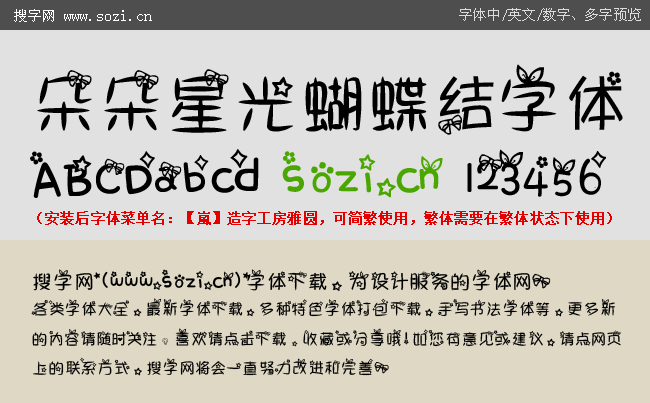
朵朵星光蝴蝶結(jié)字體
搜字網(wǎng)給大家提供一款很可愛的手機(jī)中文字體下載。字體名叫朵朵星光蝴蝶結(jié)字體,這款手機(jī)字體是以橄欖體為原形,筆畫間插入了漂亮的卡通花紋圖案。橄欖字體以橄欖為原形而設(shè)計(jì),線條粗壯,大方得體,充滿趣味性,特別適合喜歡手機(jī)字體個(gè)性一些的朋友在手機(jī)上安裝使用。